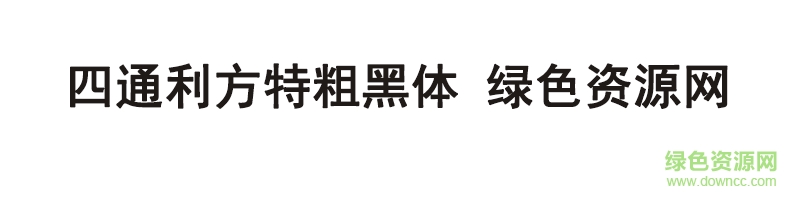
四通利方特粗黑體是專為Windows系統(tǒng)提供的一款字體更換軟件,采用了四通利方字體,字型非常粗,總體干凈利落,可應(yīng)用于廣告設(shè)計(jì)、平面設(shè)計(jì)等場(chǎng)合,歡迎來綠色資源網(wǎng)下載!
四通利方特粗黑體是黑體的一種變體,也是藝術(shù)字的一種。特點(diǎn)是筆劃更粗,盡量將空間充滿。同時(shí)為了美觀,對(duì)拐彎處的處理較為圓潤。適用于廣告、報(bào)刊等的標(biāo)題及海報(bào)展板等設(shè)計(jì)場(chǎng)合使用。